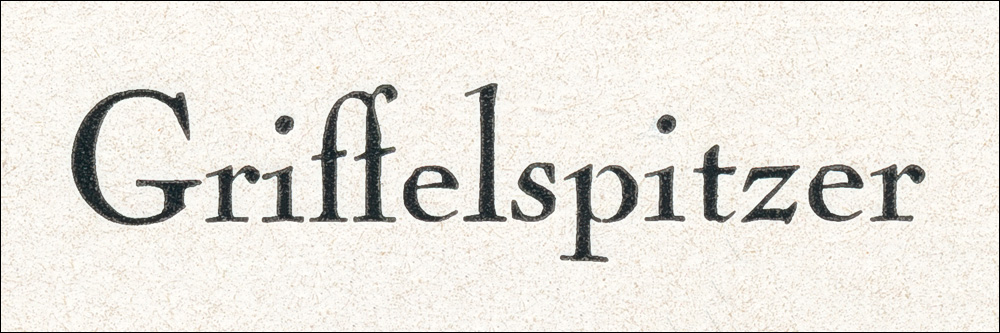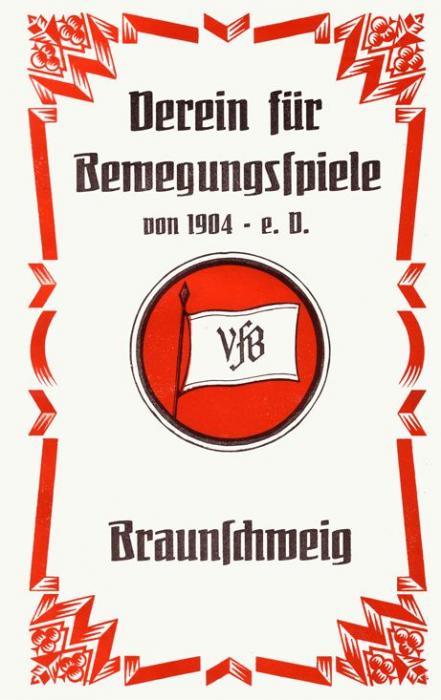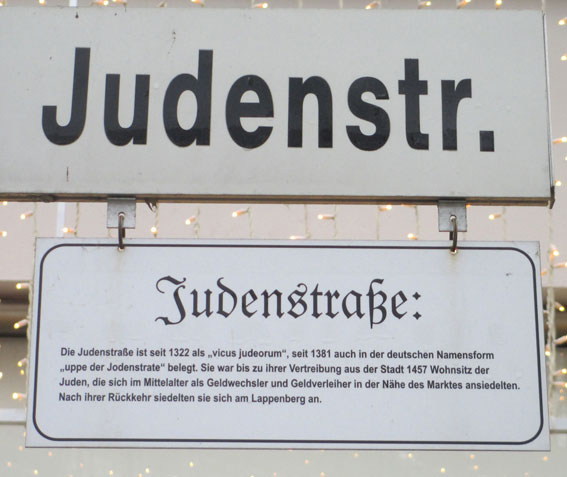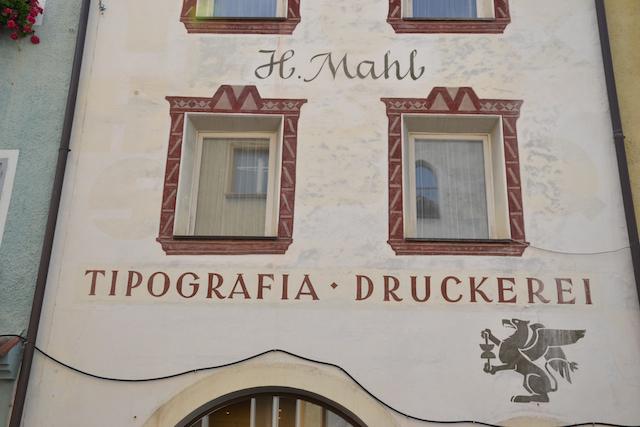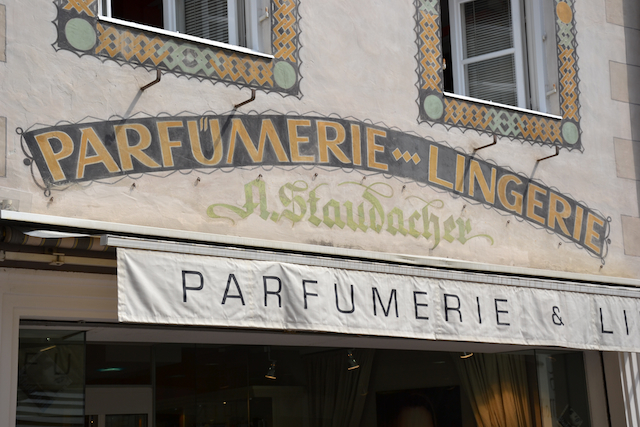
Titel der Gedenkschrift zum 100-jährigen Bestehen der Bleistiftfabrik LYRA (1906):
Aus einer Anzeige von STAEDTLER (1959):
Weiß jemand, was es mit dem Strich über dem w auf sich hat?
Das ist künstlerische Freiheit, bzw. pure Marotte des Zeichners. Es sieht halt dadurch etwas weniger nach Schulaufsatz aus. Vielleicht hat er sich optisch auch an bestimmte, meist klassizistische W-Formen angelehnt, bei denen ausladende Serifen auf dem W fast ein geschlossenes Dach bilden. Mir fällt jetzt gerade nur die (nicht wirklich klassizistische) Tiffany von Benguiat ein, aber ich meine mich zu erinnern, auch schon komplett geschlossene »Flachdächer« auf W-Formen gesehen zu haben.
Weiß jemand, was es mit dem Strich über dem w auf sich hat?
Ich kann mir auch vorstellen, dass der Strich bzw. seine Art der besseren Unterscheidbarkeit zwischen w, u und n dienen.
Hmmmh, das Argument kenn ich zur Unterscheidung des u und des n (ich selbst hab meiner Oma einen Querstrich über dem u meiner Handschrift abgeguckt und bis heut nimmer abgelegt). Zusätzlich über dem w angebracht scheint mir das aber eine Erschwernis beim Lesen. Und hilft sowieso nur dem, der daran gewöhnt ist ...
Titelseite einer Vereinszeitschrift aus dem Jahre 1925
Schrift: »Bombe« von Otto Ludwig Nägele
Gießerei: Ludwig & Mayer, Frankfurt am Main, 1908
Hmmmh, das Argument kenn ich zur Unterscheidung des u und des n
Eine Weile gab es hier ein Ladenschild mit "fōn" drauf, In Anlehnung an n/u habe ich mich da auch gefragt, wovon da unterschieden werden sollte. Oder was da verdoppelt werden sollte (beim m gelegentlich so). Leider nicht geknippst, inzwischen glaub anderes Schild.
Eine Weile gab es hier ein Ladenschild mit "fōn" drauf, In Anlehnung an n/u habe ich mich da auch gefragt, wovon da unterschieden werden sollte.
Vielleicht wurde das aus angelsächsischen Raum importiert. Hier sieht man das ab und zu bei Begriffen, deren Schreibung zu Marketingzwecken  :hammer:  verfremdet – meist verkürzt – wurde. Das Makron dient i.a.R. dazu, den Leser darauf hinzuweisen, dass der Vokal lang ausgesprochen werden soll – letztendlich also dazu, das Wort trotz der verfremdeten Schreibung über die Aussprache weiterhin entzifferbar zu machen.
Normalerweise wird im Englischen ein langer Vokal durch ein dem nächsten Konsonanten folgendes e gekennzeichnet, vgl. hat/hate, ton/tone, tin/tine, strip/stripe usw. usf. Soll das Wort phone, um das es hier sehr wahrscheinlich geht, zu fon verkürzt werden, würden die meisten Leser es intuitiv mit kurzem Vokal aussprechen. Durch das Makron wird der Vokal hingegen wieder lang und fōn damit zu einem Homophone von phone. Warum das funktioniert, obwohl die übergroße Mehrheit der Angelsachsen keine Sprache spricht, in der das Makron so benutzt wird, weiß ich nicht, aber irgendwie funktioniert es trotzdem.
Fōn habe ich schon selbst gesehen, und andere Anwendungen sind denkbar, z.B. so was wie The Tōn Store für ein Musikladen oder auch Don’t hāt für eine Toleranzkampagne. In Pennsylvania gibt es ein Skigebiet namens Snö Mountain. Da wird derselbe Effekt durch einen Umlaut statt Makron erzeugt.
Warum das funktioniert, obwohl die übergroße Mehrheit der Angelsachsen keine Sprache spricht, in der das Makron so benutzt wird, weiß ich nicht, aber irgendwie funktioniert es trotzdem.
vermutlich, weil einsprachige englische wörterbücher aus dem angloamerikanischen raum häufig respelling-systeme verwenden, um die aussprache der lemmata anzugeben. in vielen (teilweise online zugänglichen) wörterbüchern wird ›tone‹ als ›tōn‹ transkribiert. der liste in der wikipedia entnehme ich, dass es sogar ältere aussprachewörterbücher gibt, die solche systeme verwenden – wohingegen sich selbst in älteren europäischen publikationen eher (veralteter versionen) des internationalen phonetischen alphabets bedient wurde.
Durch das Makron wird der Vokal hingegen wieder lang und fōn damit zu einem Homophone von phone.
Zur Aufklärung: Im Laden gab's keine Telephone, sondern abgeschnittene Löckchen, womit naheliegend sein sollte, was der Makron eigentlich mal war, bevor die zwei zum Makron umgedengelt wurden ... ;-)
Aber interessant, was man über diesen Weg über das Amerikanische dazu lernt ;-)
Ich merke, ich muss dringend mal Urlaub machen. Anscheinend haben hier wieder mal extreme Fälle …
vermutlich, weil einsprachige englische wörterbücher
… von Betriebsblindheit – ich habe ständig mit genau solchen Wörterbüchern zu tun –
Im Laden gab's keine Telephone, sondern abgeschnittene Löckchen
… und zu viel Englisch zugeschlagen, dass mir der so naheliegende deutsche Fön nimmt einfiel. 8-)
Donald E. Knuth’s Diamond-shape-sign-Sammlung
Insgesamt gibt’s dort über 1000 verschiedene Schilder. Für alle die’s nicht wissen; D.E. Knuth ist u.a. der Entwickler von TeX und ein Pionier der Informatik :bow:
Sind auch australische Schilder dabei ...
Außerhalb Europas hält man sich daran jedoch kaum.
Most jurisdictions outside Europe have not adopted either treaty, and maintain their own systems of road traffic signals. For example, the U.S. Manual on Uniform Traffic Control Devices (MUTCD) does not follow the symbol policy espoused by the Vienna Convention …
Da können wir ja im nächsten Sommer ein Sommerlochrätsel draus machen. Das »as« scheint mir zu Douglas zu gehören, das »ls« gehörte bestimmt mal zu einer Pils-Stube. :nicken: